ฟอนต์เปลี่ยนแบรนด์: เลือกยังไงให้ลูกค้าจำ SME ต้องรู้
การเลือกฟอนต์ที่เหมาะสมเป็นองค์ประกอบสำคัญในการสร้างแบรนด์สำหรับธุรกิจ SME ฟอนต์ไม่ได้เป็นเพียงตัวอักษรสำหรับสื่อสารข้อความ แต่ยังทำหน้าที่เป็น “เสียง” หรือ “บุคลิกภาพ” ของแบรนด์ที่สามารถสื่อสารอารมณ์ ความน่าเชื่อถือ และค่านิยมขององค์กรไปยังผู้บริโภคได้โดยไม่ต้องใช้คำพูด การเลือกฟอนต์ที่สอดคล้องกับตัวตนของแบรนด์จึงช่วยสร้างเอกลักษณ์ที่โดดเด่น เพิ่มการจดจำ และทำให้แบรนด์แตกต่างจากคู่แข่งในตลาดได้อย่างมีนัยสำคัญ
ประเด็นสำคัญ: พลังของฟอนต์ในการสร้างแบรนด์
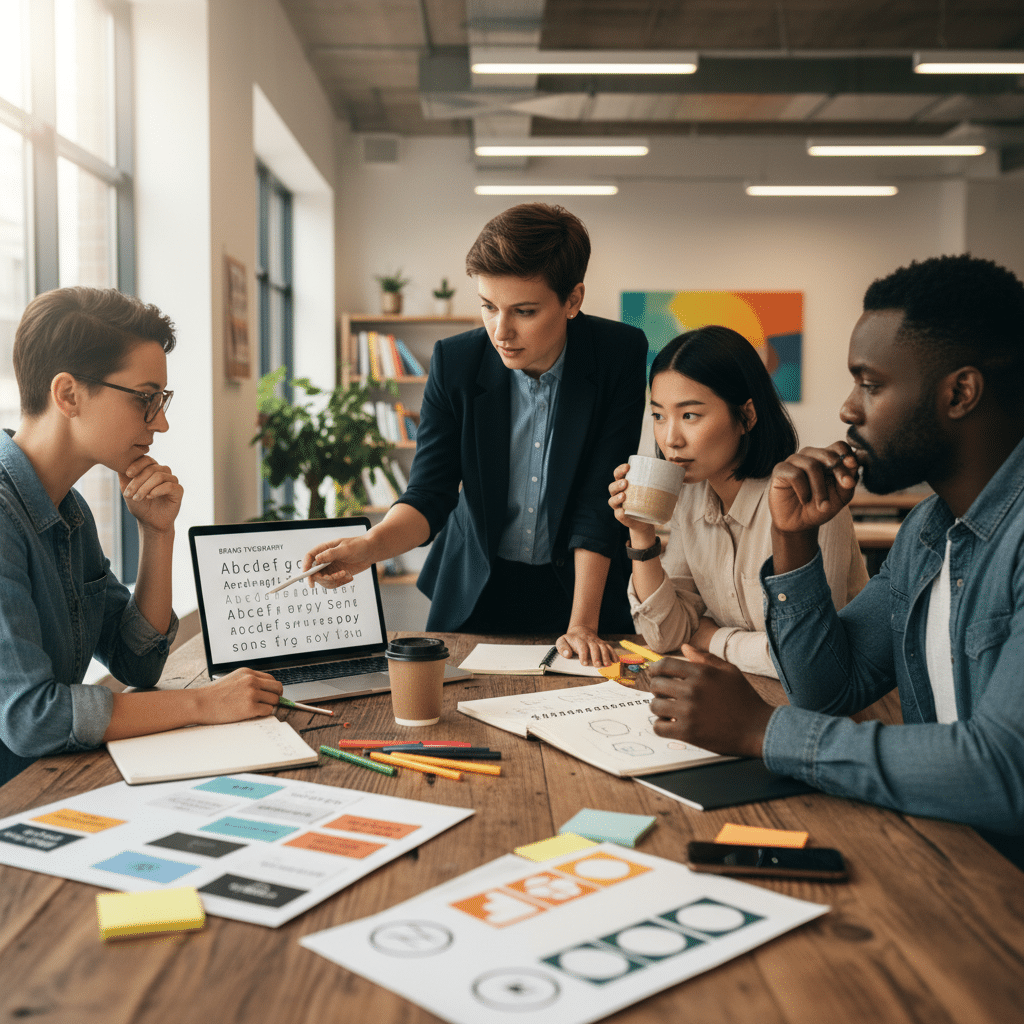
- การสร้างเอกลักษณ์: ฟอนต์ที่เหมาะสมช่วยสร้างความแตกต่างและทำให้แบรนด์เป็นที่จดจำได้ง่ายในสายตาของผู้บริโภค
- จิตวิทยาการสื่อสาร: ฟอนต์แต่ละประเภท เช่น Serif หรือ Sans Serif สามารถกระตุ้นอารมณ์และความรู้สึกที่แตกต่างกัน ซึ่งส่งผลโดยตรงต่อการรับรู้แบรนด์
- ความสอดคล้องของแบรนด์: การใช้ฟอนต์ที่เป็นระบบในทุกสื่อ ทั้งโลโก้ ฉลากสินค้า หรือสื่อดิจิทัล ช่วยสร้างภาพลักษณ์ที่แข็งแกร่งและเป็นมืออาชีพ
- ความชัดเจนในการอ่าน: ฟอนต์ที่อ่านง่ายในทุกขนาดและทุกอุปกรณ์เป็นปัจจัยพื้นฐานที่ช่วยให้การสื่อสารของแบรนด์มีประสิทธิภาพสูงสุด
- กลยุทธ์การ Rebranding: การเปลี่ยนฟอนต์เป็นเครื่องมือสำคัญในการปรับภาพลักษณ์ของแบรนด์ให้ทันสมัยและสอดคล้องกับทิศทางธุรกิจในปัจจุบัน
ทำไมฟอนต์จึงเป็นมากกว่าแค่ตัวอักษรในการสร้างแบรนด์
ในโลกของการแข่งขันทางธุรกิจที่เข้มข้น การสร้างความแตกต่างเป็นกุญแจสู่ความสำเร็จ ฟอนต์เปลี่ยนแบรนด์: เลือกยังไงให้ลูกค้าจำ SME ต้องรู้ จึงเป็นประเด็นที่ผู้ประกอบการไม่ควรมองข้าม ไทโปกราฟี (Typography) หรือศิลปะการออกแบบและจัดวางตัวอักษร มีบทบาทสำคัญอย่างยิ่งในการกำหนดอัตลักษณ์ของแบรนด์ (Brand Identity) ฟอนต์ที่ถูกเลือกใช้ในโลโก้ บนบรรจุภัณฑ์ หรือในสื่อโฆษณาต่างๆ จะกลายเป็นภาพแทนของแบรนด์ ที่สามารถสร้างความประทับใจแรกและส่งผลต่อการตัดสินใจของลูกค้าได้โดยไม่รู้ตัว
เสียงที่มองเห็นได้: บทบาทของไทโปกราฟีต่อภาพลักษณ์ธุรกิจ
ไทโปกราฟีทำหน้าที่เป็น “เสียง” ของแบรนด์ที่สื่อสารกับลูกค้าผ่านการมองเห็น ก่อนที่ลูกค้าจะอ่านข้อความ พวกเขาจะ “รู้สึก” ถึงบุคลิกของแบรนด์จากรูปแบบของตัวอักษรเสียก่อน ฟอนต์ที่มีความโค้งมนอาจให้ความรู้สึกเป็นมิตรและเข้าถึงง่าย ในขณะที่ฟอนต์ที่มีเส้นสายเฉียบคมอาจสื่อถึงความเป็นทางการและความน่าเชื่อถือ ดังนั้น การเลือกฟอนต์จึงเป็นกระบวนการเชิงกลยุทธ์ที่ต้องพิจารณาว่าแบรนด์ต้องการสื่อสารอะไร ใครคือกลุ่มเป้าหมาย และภาพลักษณ์ที่ต้องการสร้างเป็นแบบไหน การตัดสินใจนี้มีความสำคัญอย่างยิ่ง โดยเฉพาะเมื่อแบรนด์ต้องการปรับปรุงภาพลักษณ์ (Rebranding) เพื่อให้เข้ากับยุคสมัยหรือขยายสู่ตลาดใหม่
ความสำคัญของฟอนต์ต่อแบรนด์ SME ในยุคดิจิทัล
สำหรับธุรกิจขนาดกลางและขนาดย่อม (SME) ที่มีงบประมาณจำกัด การลงทุนกับการเลือกฟอนต์ที่เหมาะสมถือเป็นการสร้างความได้เปรียบทางการตลาดที่คุ้มค่าและยั่งยืน โดยมีความสำคัญในหลายมิติ
สร้างเอกลักษณ์ที่แตกต่างและน่าจดจำ
ในตลาดที่มีสินค้าและบริการคล้ายคลึงกันจำนวนมาก ฟอนต์ที่เป็นเอกลักษณ์จะช่วยให้แบรนด์โดดเด่นออกมาจากคู่แข่ง การมีชุดฟอนต์หลักที่ใช้ในทุกการสื่อสารทำให้ผู้บริโภคสามารถจดจำแบรนด์ได้ง่ายขึ้น แม้จะเห็นเพียงแค่ตัวอักษรก็ตาม แบรนด์ระดับโลกหลายแห่งถึงกับลงทุนออกแบบฟอนต์เฉพาะ (Custom Font) เพื่อป้องกันการลอกเลียนแบบและสร้างสินทรัพย์ทางปัญญาที่เป็นของตนเองโดยสมบูรณ์
เสริมสร้างความน่าเชื่อถือและภาพลักษณ์ระดับมืออาชีพ
การเลือกใช้ฟอนต์อย่างมีหลักการและสอดคล้องกันในทุกสื่อ แสดงให้เห็นถึงความใส่ใจในรายละเอียดและความเป็นมืออาชีพของแบรนด์ สิ่งนี้ช่วยสร้างความไว้วางใจและความน่าเชื่อถือให้กับลูกค้า โดยเฉพาะในธุรกิจที่ต้องการสร้างภาพลักษณ์หรูหราและพรีเมียม เช่น แบรนด์แฟชั่น เครื่องสำอาง โรงแรม หรือบริการทางการเงิน ฟอนต์ที่สง่างามและคลาสสิกสามารถยกระดับการรับรู้ของลูกค้าที่มีต่อแบรนด์ได้อย่างมาก
ปรับปรุงประสิทธิภาพการสื่อสารในทุกแพลตฟอร์ม
ฟอนต์ที่ดีต้องทำหน้าที่พื้นฐานที่สุดคือการสื่อสารข้อความได้อย่างชัดเจน การเลือกฟอนต์ที่อ่านง่าย (Readable) ในทุกขนาด ตั้งแต่ขนาดเล็กบนฉลากสินค้าไปจนถึงขนาดใหญ่บนป้ายโฆษณา เป็นสิ่งจำเป็นอย่างยิ่ง ในยุคดิจิทัล ฟอนต์ยังต้องแสดงผลได้อย่างคมชัดบนหน้าจอทุกประเภท (Legibility) เพื่อมอบประสบการณ์ที่ดีให้กับผู้ใช้งานบนเว็บไซต์และแอปพลิเคชัน การวางแผนเรื่องฟอนต์ตั้งแต่ต้นยังช่วยประหยัดต้นทุนในระยะยาว เพราะไม่ต้องเสียเวลาและค่าใช้จ่ายในการแก้ไขงานออกแบบในภายหลัง
หลักการเลือกฟอนต์สำหรับ SME: 5 ขั้นตอนสู่แบรนด์ที่ดูโปร
การเลือกฟอนต์ไม่ใช่เรื่องของความชอบส่วนตัว แต่เป็นกระบวนการที่ต้องอิงกับกลยุทธ์ของแบรนด์เป็นหลัก ผู้ประกอบการ SME สามารถใช้หลักการ 5 ข้อนี้เป็นแนวทางในการตัดสินใจ
1. สะท้อนบุคลิกและค่านิยมหลักของแบรนด์
ขั้นตอนแรกคือการทำความเข้าใจตัวตนของแบรนด์ให้ชัดเจน แบรนด์ของคุณมีบุคลิกแบบไหน? เป็นทางการ, สนุกสนาน, ทันสมัย, หรือคลาสสิก? ค่านิยมหลักของแบรนด์คืออะไร? ความน่าเชื่อถือ, นวัตกรรม, หรือความเรียบง่าย? คำตอบเหล่านี้จะเป็นเข็มทิศในการเลือกสไตล์ฟอนต์ที่เหมาะสม เช่น แบรนด์ที่เน้นความหรูหราอาจเลือกใช้ฟอนต์ประเภท Serif ที่ดูภูมิฐาน ในขณะที่แบรนด์เทคโนโลยีที่ต้องการสื่อถึงความทันสมัยอาจเลือกใช้ฟอนต์ Sans Serif ที่ดูสะอาดตา
2. ทดสอบการอ่านง่าย (Readability) ในทุกขนาดและสื่อ